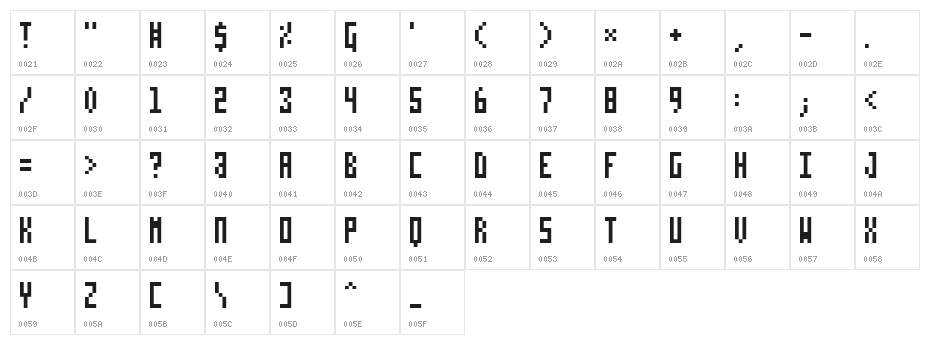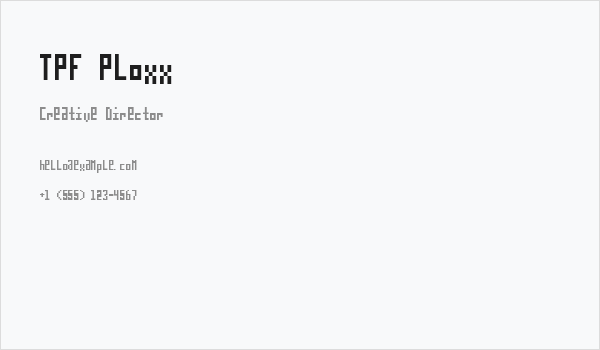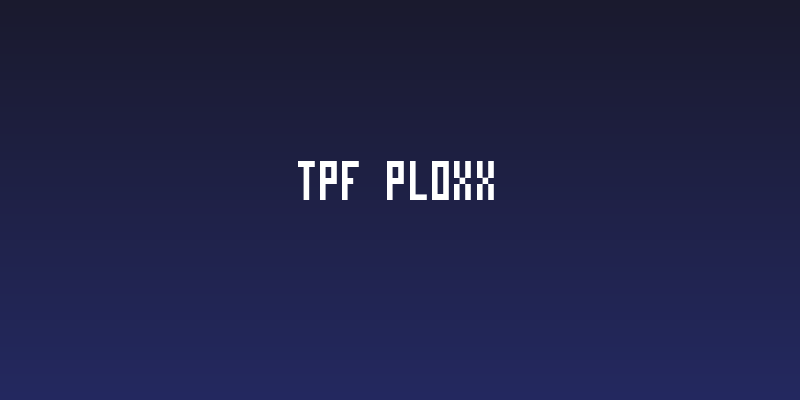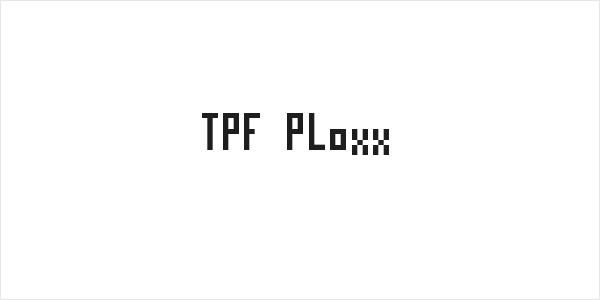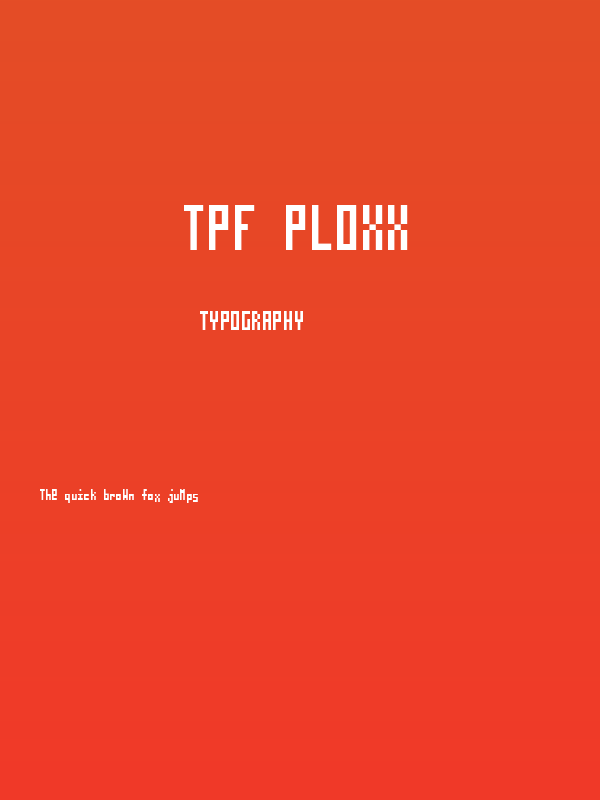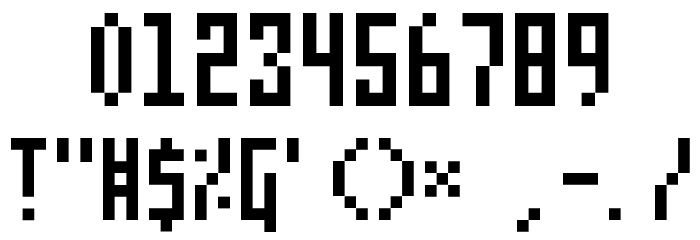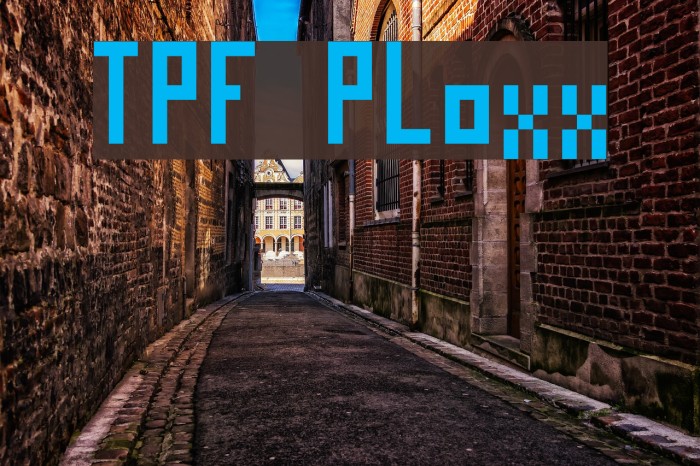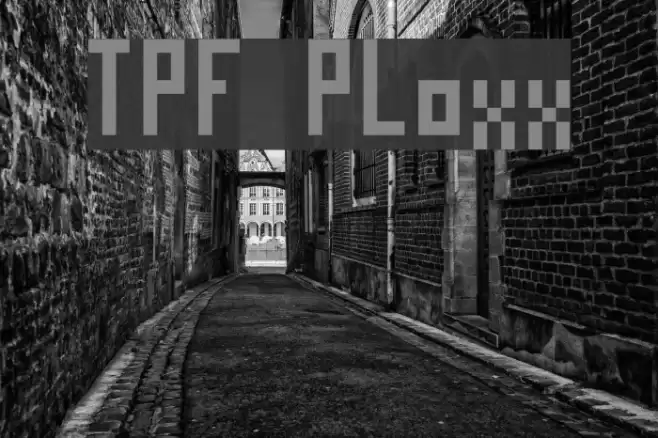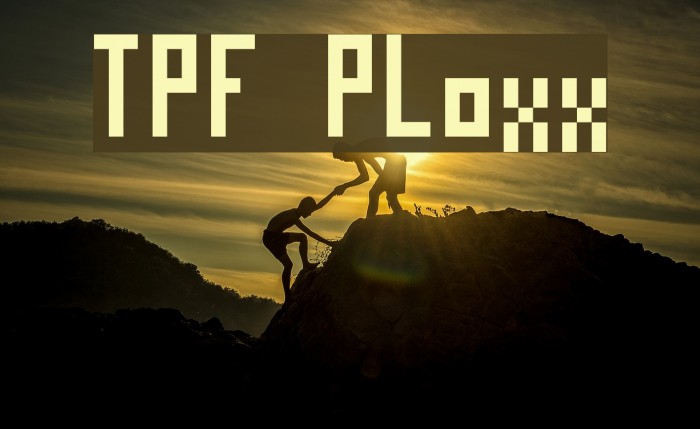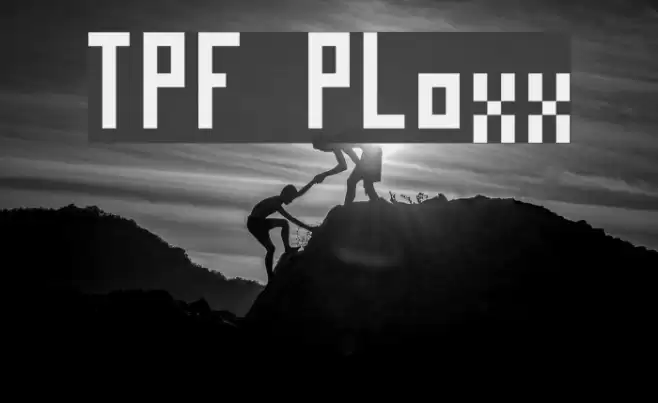
TPF Ploxx Font
| カテゴリ | Pixel |
| 文字間隔 | Normal |
| 全体的なスタイル | Retro, Digital |
| 用途 | Headlines, Logos, Digital Art |
| おすすめプロジェクト | Ideal for video game design, retro-themed posters, digital art projects, and any creative work that requires a nostalgic, digital aesthetic. |
| 等幅 | Yes |